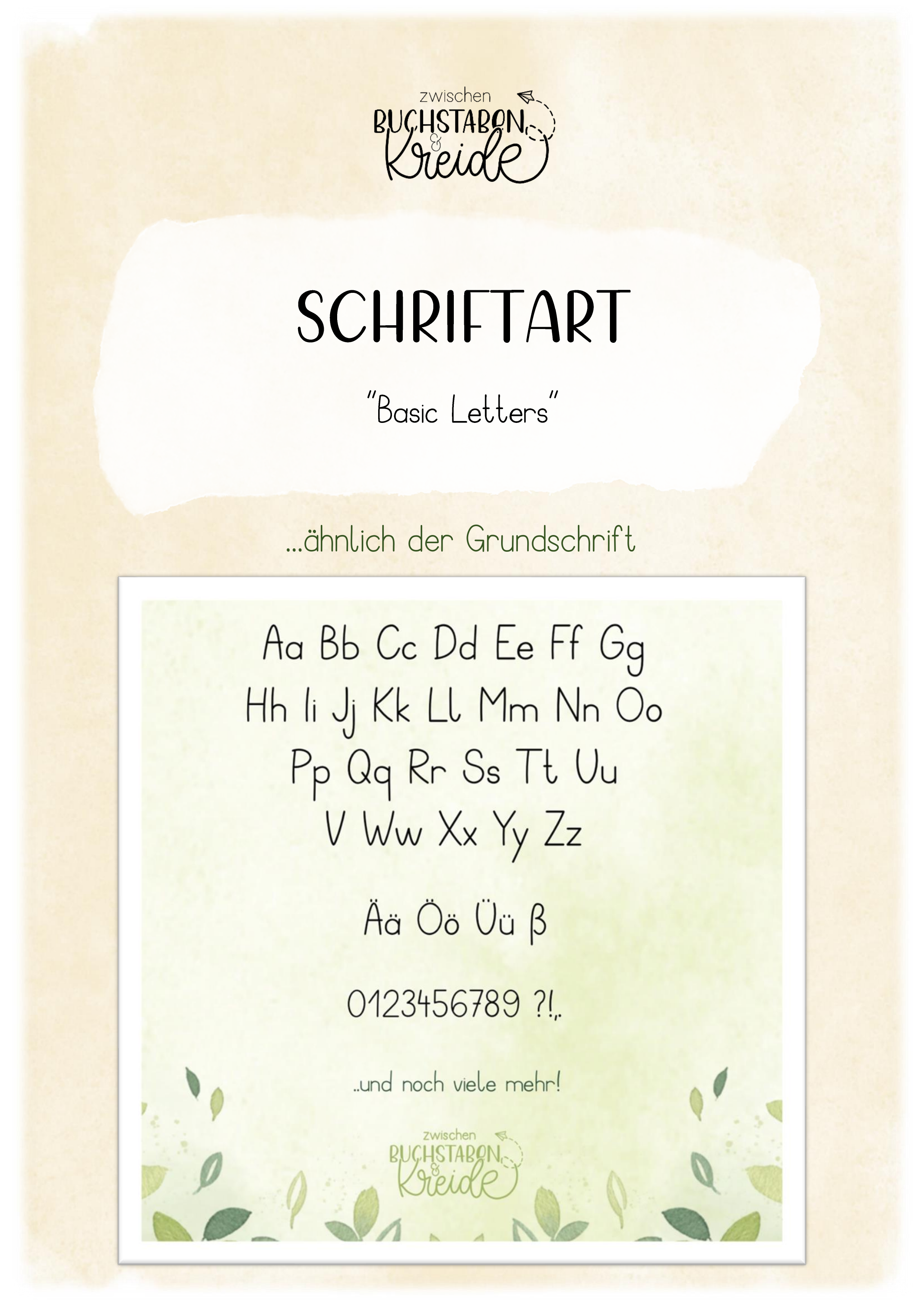
selbst erstellte Schriftarten - Schriftart "Basic Letters" - Grundschrift - zwischenbuchstabenundkreide - Deckblatt
Die Schrift ist der Grundschrift absichtlich sehr ähnlich, sodass sie auch von den Jüngsten gut gelesen werden kann.
Schriftart "Basic Letters" - Grundschrift